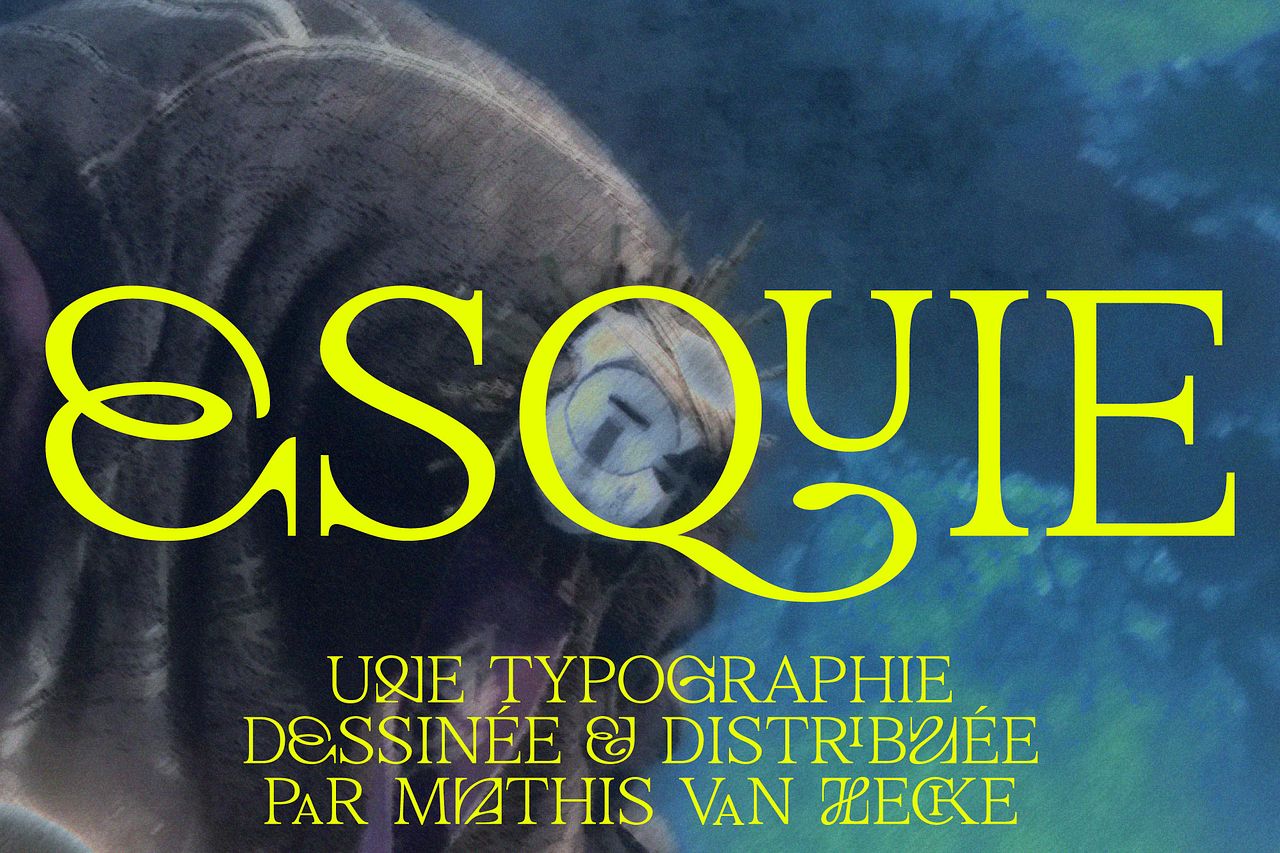
Esquie — typeface
Esquie est une typographie à empattements décorative qui joue sur le contraste et l’expression. Elle propose deux jeux de lettres complémentaires : l’un classique et équilibré, l’autre plus développé et expressif, offrant la possibilité de créer des décalages subtils ou des compositions visuelles audacieuses. Son nom ainsi que les images utilisées proviennent de l’univers poétique de Clair-Obscur: Expédition 33.